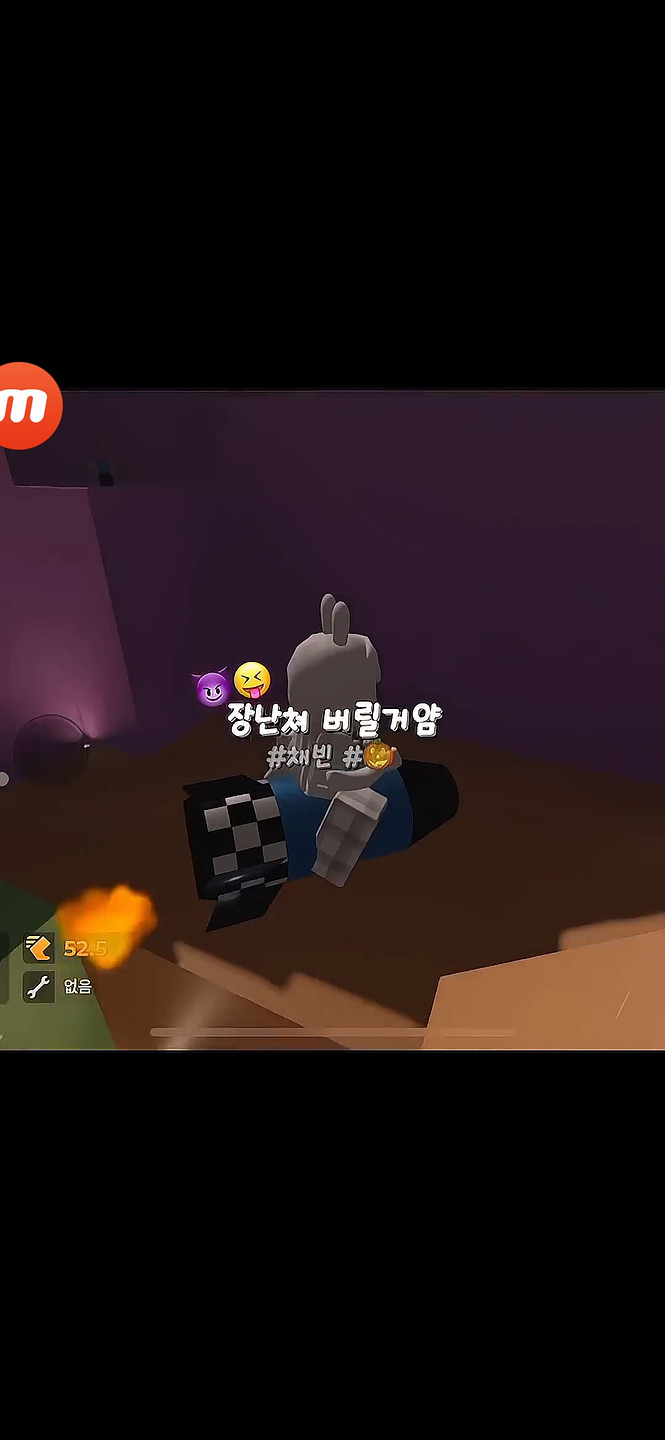
사진 속 폰트 뭔지 아시는 능력자분 계신가요..? 고딕체인데 모음 윗부분만 살짝 꺾인 고딕체... 비슷한 느낌으로 [HU메리쫑쫑 170] 을 찾긴 했는데 기본체 자체가 달라서; 많이 찾아봤지만 안나오는 거 보면 어딘가 팩에 포함되어 있는 폰트같은데 혹시 아시는 분 계시면 알려주시면 감사하겠습니다..!
이스타체 이스타항공